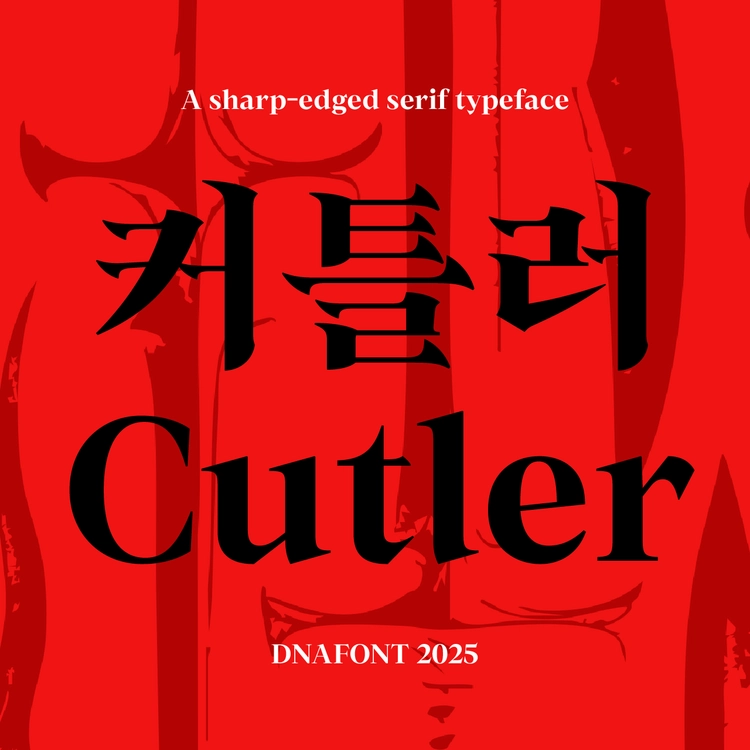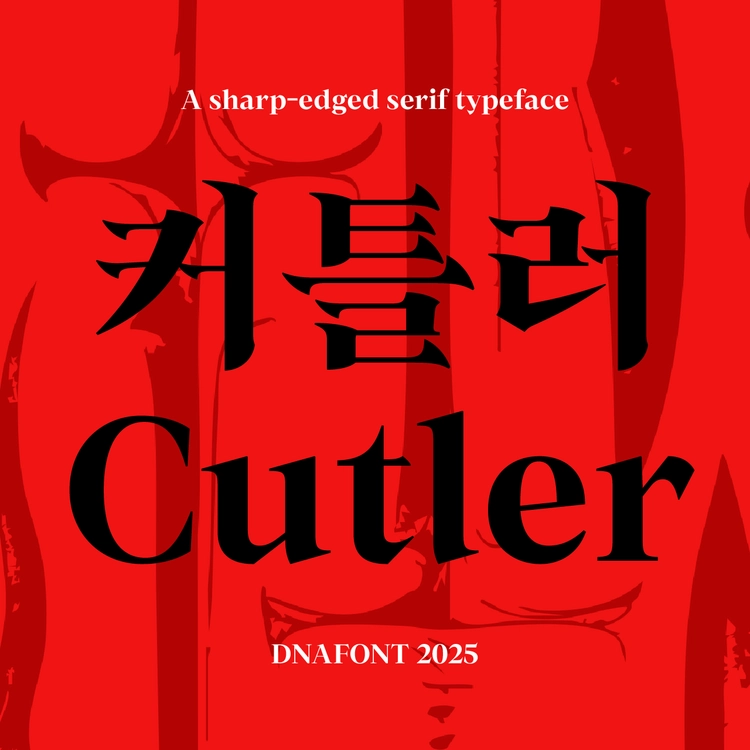
큰 획 대비와 날카롭게 강조된 세리프를 통해 벼려낸 날붙이의 인상을 담은 제목용 폰트입니다.
대장간에서 쇳덩이를 두드리고 갈아내어 검과 나이프 처럼 빛나는 무기로 완성하는 과정을 형상화했습니다.
강인하고 예리한금속의 이미지를 전하며,
날렵한 인상 덕분에 판타지 장르의 화려한 분위기까지 소화할수 있는 매력을 지녔습니다.